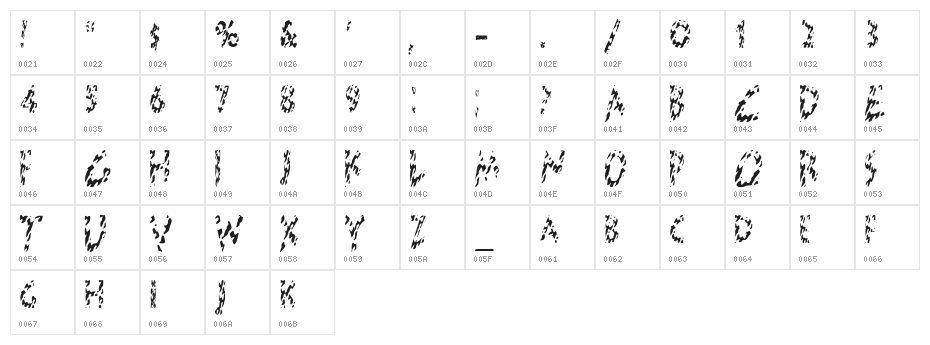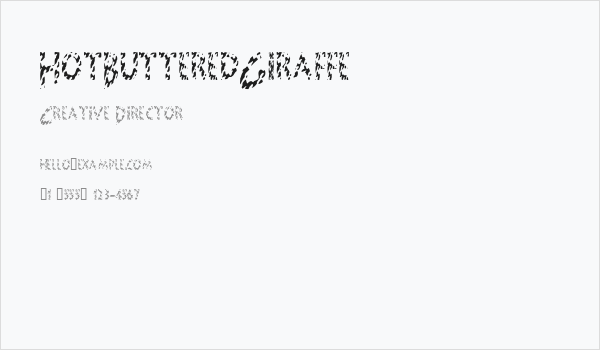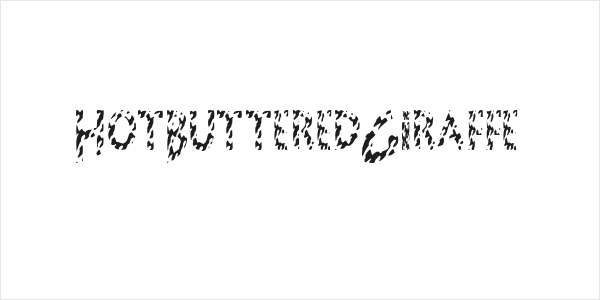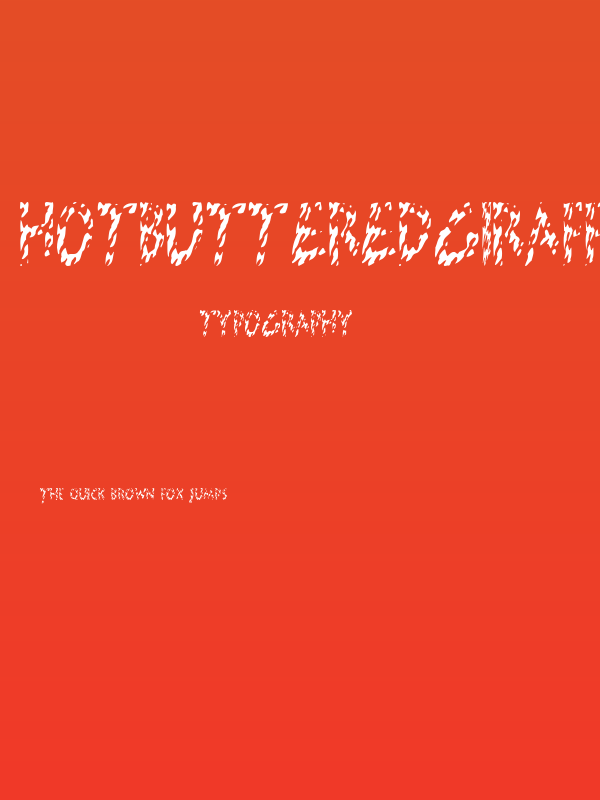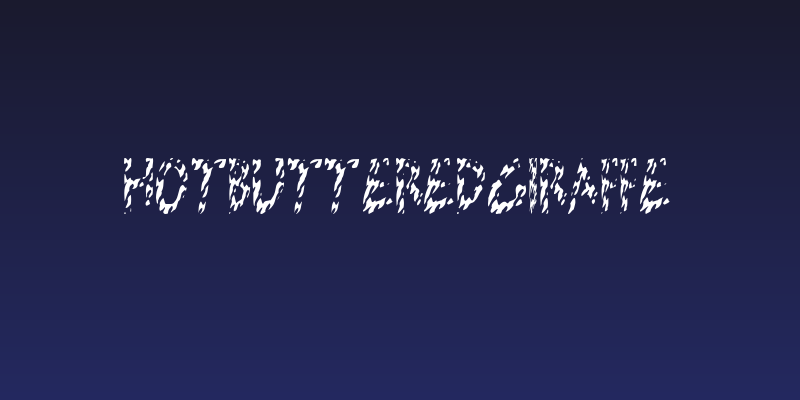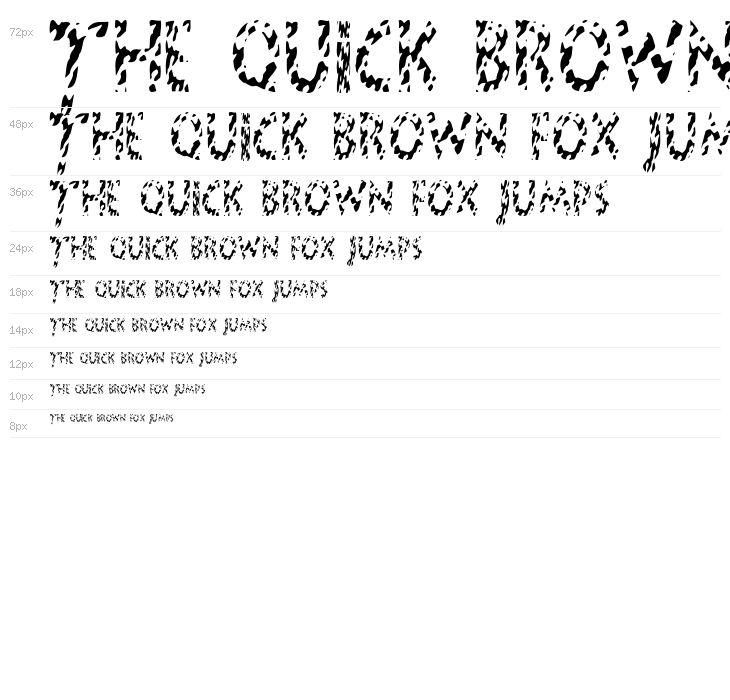
HotButteredGiraffe Font
| Vorgeschlagene Projekte | Ideal for children's book covers, playful branding, event posters, and creative packaging designs. |